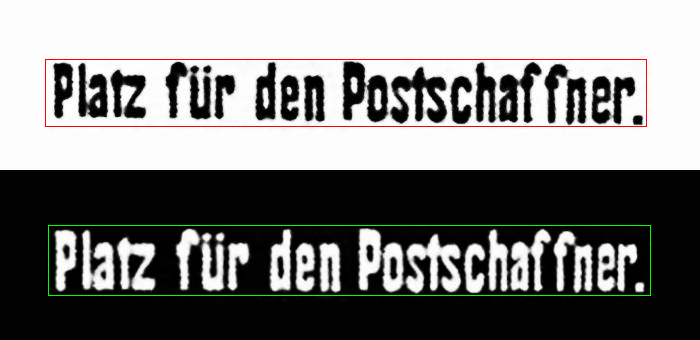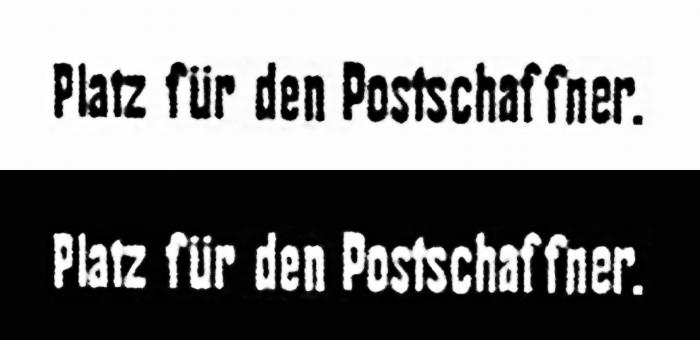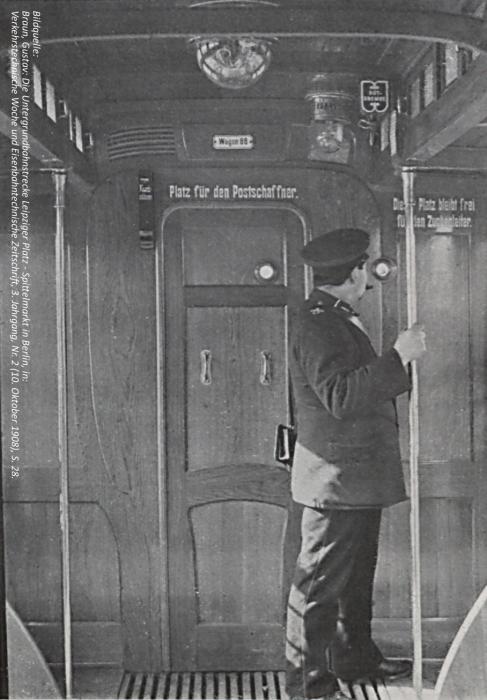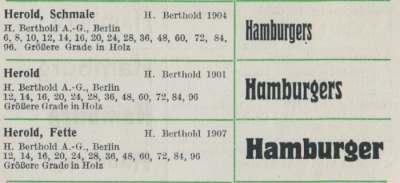
Jugendstil-Beschriftung aus Berliner U-Bahn, 1908
ich habe mich hier im Forum registriert, da ich denke, mit meinem Problem hier an der richtigen Stelle zu sein:
Mit Wagen 86 wird durch Ehrenamtliche schon seit einigen Jahren der älteste U-Bahntriebwagen Berlins (und Deutschlands) zurück in seinen Auslieferungszustand von 1908 versetzt.
Nach Abschluss der Arbeiten soll er auch wieder zu besonderen Anlässen seine Runden durch Berlins Untergrund drehen.
Am Wagen waren (und sind) umfangreiche Arbeiten durchzuführen. (Notwendige) Umbauten und Rückbauten der letzten hundert Jahre sowie letztendlich die Abstellung Ende der 1960er Jahre im Freien und seine Verwendung als Aufenthaltsraum haben deutliche Spuren hinterlassen.
Auf einer zeitgenössischen Fotografie ist die Führerstandsrückwand mit ihren Beschriftungen (konkret: "Platz für den Postschaffner." & "Dieser Platz bleibt frei für den Zugbegleiter.") deutlich zu erkennen (angehängtes Bild). Das Problem ist die verwendete Schriftart. Leider lassen sich keinerlei Dokumente finden, die einen Hinweis darauf geben könnten, was hier als Vorlage diente (das BVG-Archiv wurde 1943 bei einem Luftangriff schwer getroffen).
Die angehängte Fotografie stammt aus einer Zeitschrift, daher die mäßige Bildqualität. Dazu kommt noch, dass es sich wohl um das einzige Foto handelt, auf der die Beschriftung zu erkennen ist. Abgebildet ist ein "Schwester"-Fahrzeug des Erhaltenen (gleiche Lieferung/Serie).
Die 10 "Selbsthilfe"-Tricks habe ich schon durchprobiert. Leider macht hier wohl die kleine Auflösung des Bildes Probleme.
In den Fontlisten habe ich auch schon nachgesehen, wobei ich mir allerdings nicht zu traue abzuschätzen, was hier "ähnlich" ist.
Bei der Beschriftung handelt es sich ja nicht um eine Drucksache, meine Hoffnung beruht allerdings darauf, dass sie vielfach ausgeführt werden musste und nicht nur einmal, was das Vorhandensein einer "Vorlage" einigermaßen wahrscheinlich machen könnte.
Sämtliche Informationen, die evtl. nützlich sein könnten:
- Der Wagenkasten wurde 1908 in der Waggonfabrik Falkenried, Hamburg hergestellt.
- Das gesamte Fahrzeug weißt noch (leicht) die Formensprache des Jugendstils auf.
Es wäre wirklich klasse, wenn jemand von euch eine Ahnung hätte, welche Schriftart das hier sein könnte bzw. an welcher Schriftart sich das orientiert.
Phantastisches Projekt!
erste Frage: gibt es (physisch) irgendwelche Restspuren der Beschriftung, die man analysieren könnte?
zweite Frage: wie wurde die Beschriftung aufgebracht? Eingedenk der Zeit hier naheliegend:
• a) Beschriftung mit Pinsel von Hand
• b) Schablonierarbeit/Stupfpinsel
– Folienplots gab’s 1908 noch nicht :neenee:
Was es aber gab: Satzschriften (Blei oder Holz), die in etwa so aussahen. Werde in Kürze mal in einem bestimmten Schriftmusterbuch nachsehen, ob sich dort etwas ähnliches findet.
Sieht so ein bisschen nach der "Herold" aus, ist allerdings zu unscharf, um zu erkennen, ob es nicht vielleicht doch ne Groteske im "Herold"-Style ist ...
gibt es (physisch) irgendwelche Restspuren der Beschriftung, die man analysieren könnte? [...]
Leider nein. - Mitte '49 wurde die ursprüngliche Rückwand ausgebaut und ersetzt. Zu diesem Zeitpunkt wurden die Wagen intern schon als "Stehwagen" bezeichnet. Der nur knapp mehr als 90 Zentimeter lange Führerstand gestattet(e) es kaum, bequem zu stehen, geschweige denn eine Sitzmöglichkeit unterzubringen. Verschärfte Sicherheitsbestimmungen verlangten außerdem, dass der Zugbegleiter ein "eigenes" Fenster an der Front bekommen sollte. Bei der jetzigen Wand handelt es sich um eine Rekonstruktion anhand von (Werks-)Fotografien.
Zugegebenermaßen kann ich nicht beantworten wie die Hinweise aufgebracht wurden, deswegen möchte ich auch nicht mutmaßen. Möglich wäre natürlich beides. Andere Beschriftungen (im Führerstand selbst, von denen ich momentan leider keine Fotos zur Hand habe) scheinen eindeutig "von Hand" angebracht worden zu sein, was nicht zwangsläufig etwas zu heißen hat.
...auf Folienplots wird es wohl hinauslaufen. :-) Wenngleich klassisches Handwerk richtig beherrscht natürlich Eindruck machen würde.
Sieht so ein bisschen nach der "Herold" aus [...]
Danke für den Hinweis! Unter Umständen wäre das sogar ein annehmbarer Kompromiss (wenn überhaupt), wenn alles andere im Sand verläuft. ...der Abdruck des Bildes in einer zeitgenössischen Zeitschrift ist wie erwähnt die einzige Quelle und noch dazu ein echter Glücksfall.
Die verwendete Schriftart auf dem Rollband ("Harburg Moorstr.") sieht unserer doch ähnlich? Was meint ihr? In den entsprechenden Vereinen, lässt sich ein solches Band eventuell ja sogar noch finden.